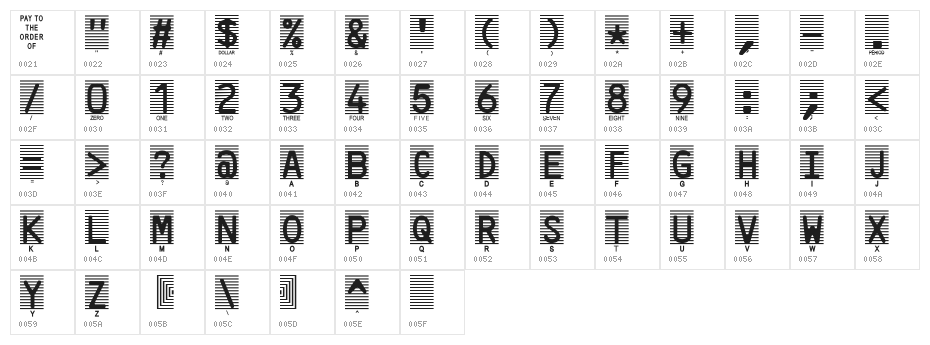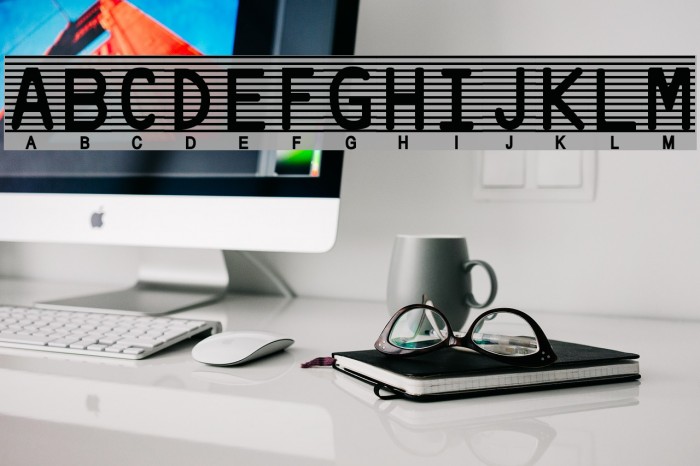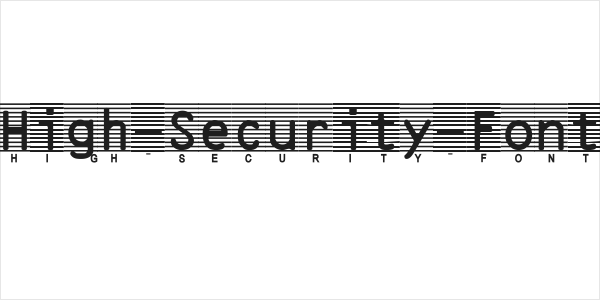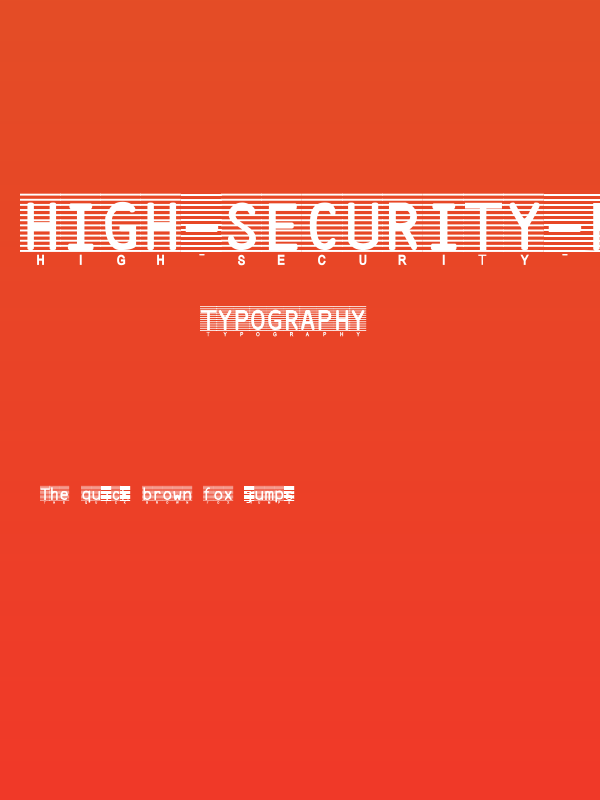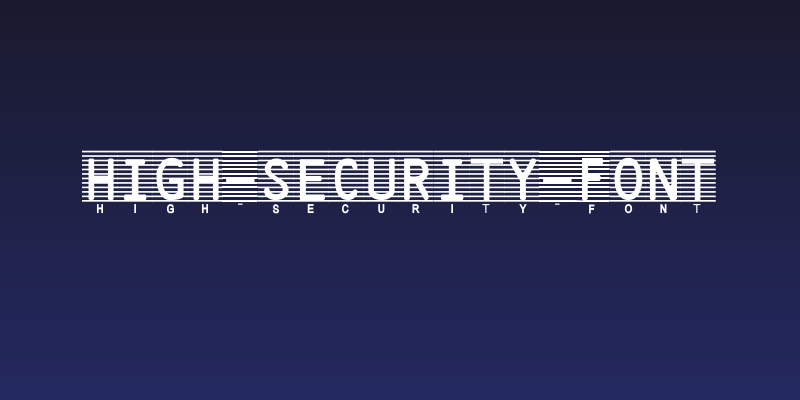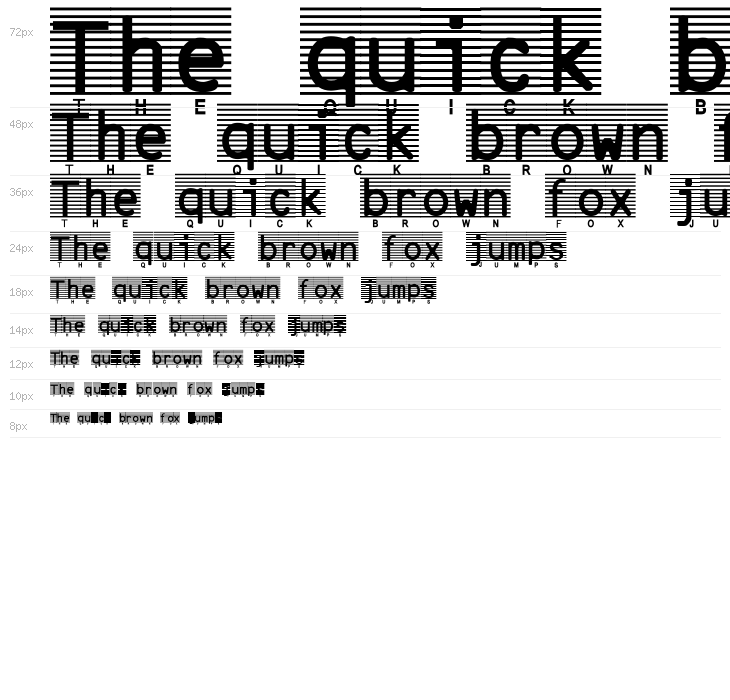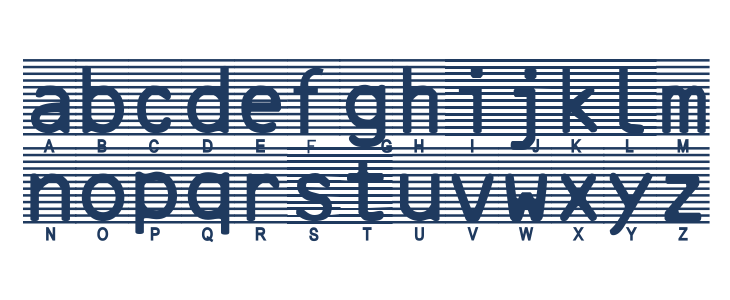
High-Security-Font Font
✎ Typewriter
| Anwendungsfall | Security documents, Legal paperwork, Checks |
| Vorgeschlagene Projekte | Ideal for use in security documents, checks, legal paperwork, and any application requiring precise character recognition. |